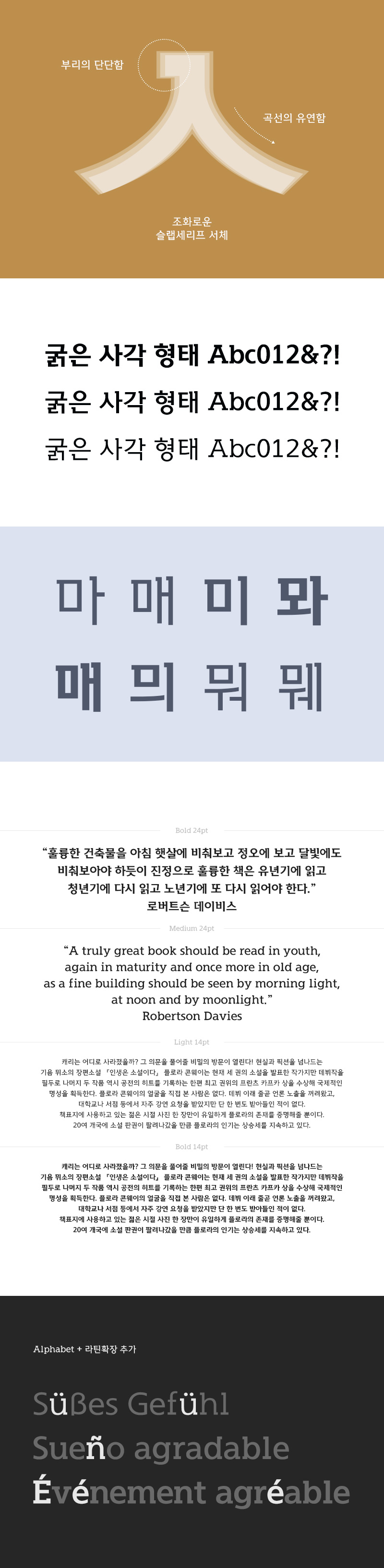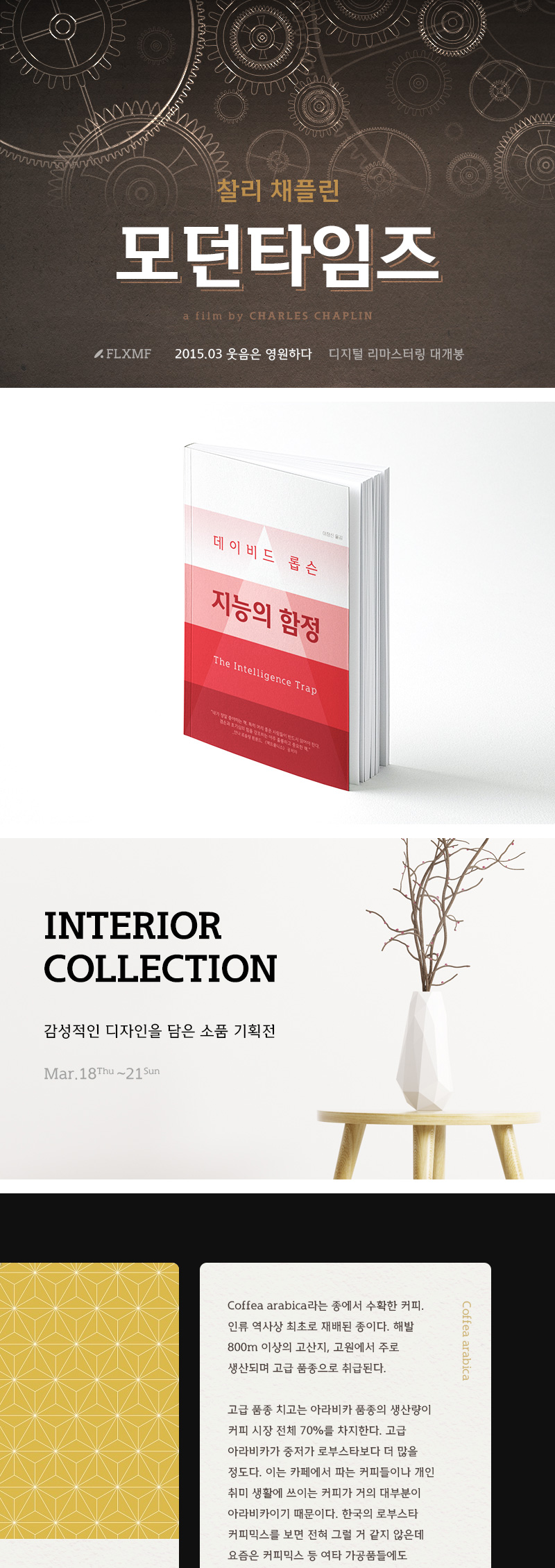
RixModernTimes
3 Style - Bold, Medium, LightRix모던타임즈는 굵은 직사각 형태의 슬랩 세리프와 유연한 곡선 획의 조화가 특징인 서체입니다.
사용성을 높인 3종의 웨이트로 획의 두께에 따라 다양한 느낌을 연출할 수 있습니다.
특유의 단정하고 간결한 형태가 북 커버, 포스터 등 각종 인쇄물의 텍스트나 영상의 자막으로 활용하기 좋습니다.
| FontFamily | Rix모던타임즈 / RixModernTimes |
| Design | Kim Su-jung |
| Direction | Park Yong-rak |